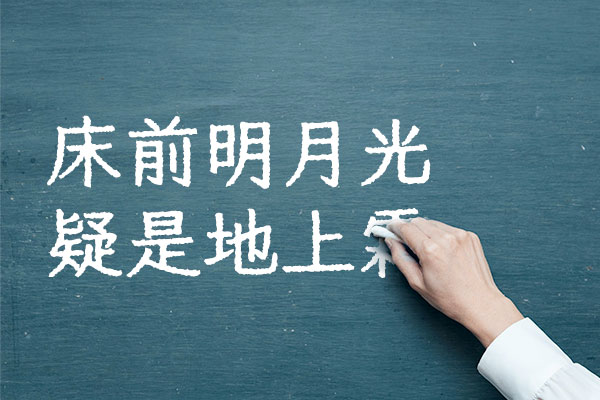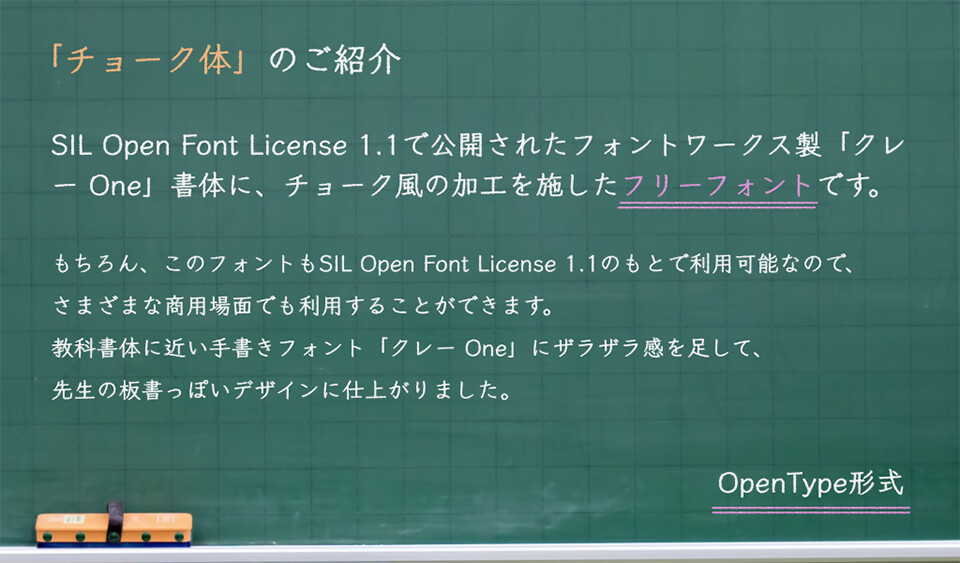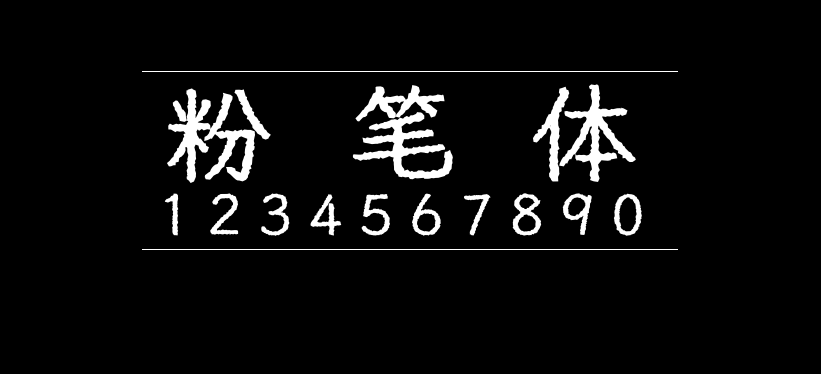
粉笔体
粉笔体(チョーク体、Chalk JP)是基于Fontworks系列免费字体克利Klee One字体进行二次创作产生的衍生字体,给字体的边缘加上破损效果,让字体看起来像粉笔字写到黑板上一样的触感。
粉笔体字体由于是日本人推出的字体,所以其字符以日文为主,中文字符部分繁体支持得还不错,简体字存在缺字现象。